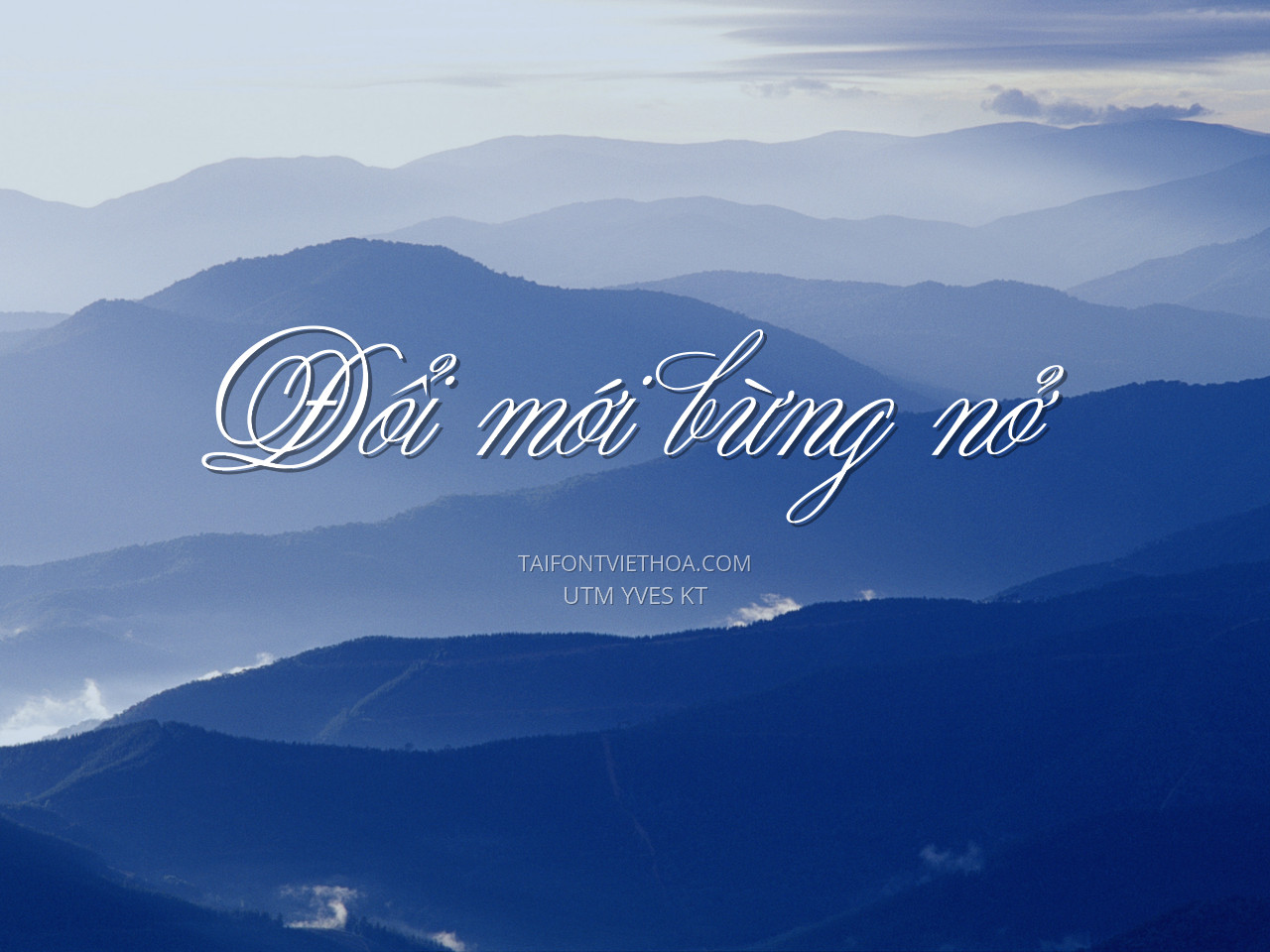
Font việt hóa UTM Yves KT đầy đủ
Giới thiệu về font UTM Yves KT đầy đủ – Kiểu chữ script tinh tế và đa dạng
UTM Yves KT đầy đủ là phiên bản Việt hóa của bộ font Yves KT – một bộ sưu tập font script thanh lịch, mềm mại và đầy phong cách, được thiết kế dựa trên phong cách viết tay tự nhiên và bay bổng. Bộ font nổi bật với các ligature tinh xảo, đa dạng biến thể và nét bút uyển chuyển, rất phù hợp cho các dự án thiệp cưới, branding cao cấp và các sản phẩm cá nhân hóa. Phiên bản Việt hóa đã được hoàn thiện để hỗ trợ đầy đủ tiếng Việt cùng hơn 100 ngôn ngữ khác, mở rộng phạm vi sử dụng trong nhiều dự án sáng tạo.
Font UTM Yves KT đầy đủ được taifontviethoa.com sưu tầm và lựa chọn kỹ lưỡng nhằm phục vụ cộng đồng thiết kế Việt Nam. Phiên bản Việt hóa giữ nguyên nét mềm mại, duyên dáng và tinh tế của bộ font gốc, đồng thời tối ưu khả năng hiển thị tiếng Việt, rất phù hợp cho các dự án thiệp cưới, thiết kế nghệ thuật và truyền thông cá nhân hóa.
Đặc điểm thiết kế và ứng dụng của UTM Yves KT đầy đủ
UTM Yves KT đầy đủ sở hữu cấu trúc script với các nét bút thanh mảnh, linh hoạt và đa dạng ligature giúp tăng tính linh hoạt và biểu cảm trong thiết kế. Bộ font có độ tương phản nhẹ nhàng, tạo cảm giác mềm mại, bay bổng và sang trọng, rất thích hợp cho các thiết kế mang phong cách cá nhân hóa và nghệ thuật cao. Bộ font còn được trang bị nhiều glyph thay thế để tăng sự linh hoạt và đa dạng trong thiết kế.
Font thích hợp sử dụng trong các ứng dụng như thiệp cưới, thiệp mời, thiết kế logo thương hiệu mỹ phẩm, poster nghệ thuật, bao bì sản phẩm thủ công và các dự án truyền thông mang tính cá nhân hóa cao. Các ngành nghề phù hợp gồm: tổ chức sự kiện, thời trang, làm đẹp, nghệ thuật sáng tạo và quảng cáo cá nhân hóa.
Thiết kế: Mans Greback
Thiết kế: Sarid Ezra